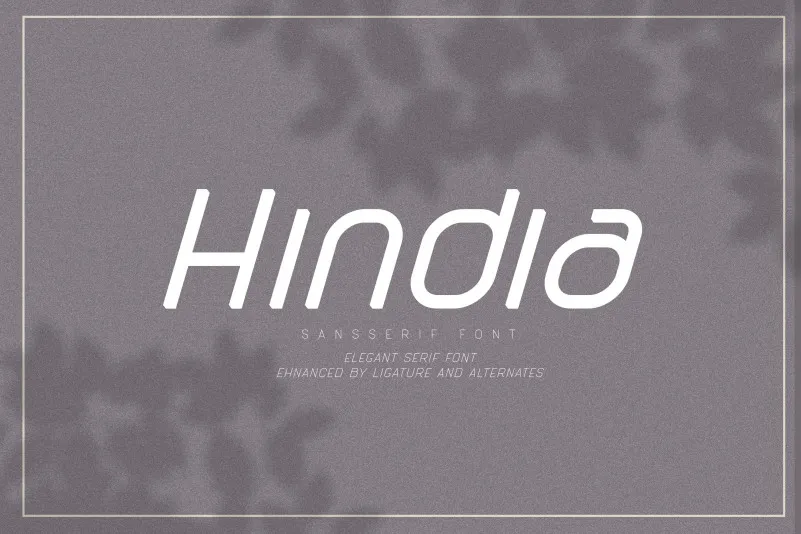
Hindia Sans Serif Font – Download Grátis
Hindia Sans Serif é uma fonte sans-serif moderna que evoca as memórias agradáveis dos verões na campina. Inspirada nos sons das risadas dos melhores amigos ao ar livre, bem como no céu estrelado perfeitamente limpo e sem nuvens à noite, essa fonte traz um pouco de aventura com seu formato monolineário. Ideal para uma série de aplicativos que incluem design gráfico, identidade visual, ou até mesmo o layout de sites. A mhdafifersya trouxe a nossa lista desta fonte elegante e moderna na categoria sans serif, certamente é um complemento perfeito à sua próxima criação digital.